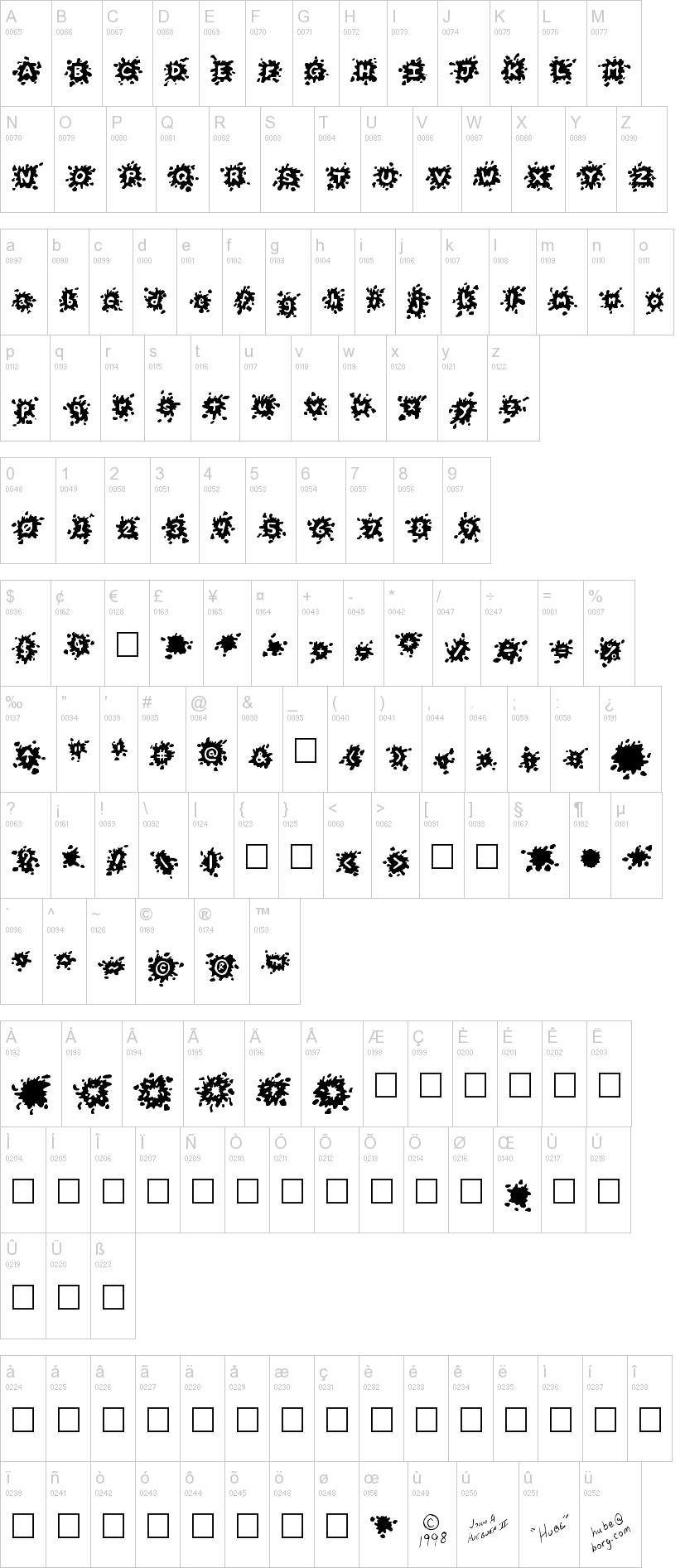
Splats
Splats字体是一种新的趣味性字体,它的特色是由一系列随机的笔触组成,形成一种复杂而有趣的图案。这种字体可以用来制作海报、T恤、标志、网页等,能够使设计更加生动有趣。Splats字体可以改变字体的外观,使它们更加有趣,令人印象深刻,并且能够提升设计的质量。
Splats是一款非常不错的手写艺术字体,具有很好的视觉感,适合于文化类的宣传设计、商业类品牌的广告和产品包装设计以及个性化文字排版等较多场景。